Làm chủ cách phối font chữ là chìa khóa để tạo nên thiết kế ấn tượng và chuyên nghiệp, ảnh hưởng trực tiếp đến hiệu quả truyền tải thông điệp. Trong thế giới thiết kế, việc lựa chọn và kết hợp các font chữ một cách hài hòa, khoa học không chỉ là vấn đề thẩm mỹ mà còn là yếu tố then chốt giúp bạn tạo ra những sản phẩm thiết kế thu hút và dễ đọc. Bài viết này, thuộc chuyên mục Blog, sẽ đi sâu vào các nguyên tắc phối font chữ, từ cách lựa chọn font chữ phù hợp với dự án, nhận diện các cặp font chữ lý tưởng, đến việc sử dụng các công cụ hỗ trợ để tạo ra sự tương phản và cân bằng thị giác trong typography. Chúng tôi sẽ cung cấp cho bạn những bí quyết phối font chữ thực chiến, dễ áp dụng, giúp bạn nâng tầm kỹ năng thiết kế và tạo ra những sản phẩm ấn tượng nhất vào năm 2025.
Tầm Quan Trọng Của Phối Font Chữ Trong Thiết Kế: Tại Sao Lựa Chọn Đúng Font Lại Quyết Định Thành Công
Trong thế giới thiết kế, việc phối font chữ đóng vai trò then chốt, không chỉ đơn thuần là lựa chọn kiểu chữ mà còn là yếu tố quyết định đến sự thành công của một dự án. Một sự kết hợp font chữ tinh tế và phù hợp có thể truyền tải thông điệp một cách hiệu quả, thu hút sự chú ý và tạo dựng ấn tượng sâu sắc cho người xem. Ngược lại, lựa chọn font chữ sai lầm có thể phá hỏng toàn bộ nỗ lực thiết kế, khiến thông điệp trở nên khó hiểu, gây mất thiện cảm và thậm chí làm giảm giá trị thương hiệu.
Vậy, điều gì khiến phối font chữ trở nên quan trọng đến vậy? Hãy cùng khám phá những khía cạnh then chốt mà việc lựa chọn đúng font chữ có thể mang lại:
- Truyền tải thông điệp hiệu quả: Font chữ có khả năng biểu đạt cảm xúc, phong cách và cá tính. Ví dụ, một font chữ serif cổ điển có thể tạo cảm giác trang trọng, đáng tin cậy, trong khi một font sans-serif hiện đại lại mang đến sự trẻ trung, năng động. Sự kết hợp hài hòa giữa các font chữ giúp làm nổi bật thông điệp chính, tạo sự rõ ràng và dễ hiểu cho người đọc. Theo nghiên cứu của Baymard Institute, 80% người dùng đánh giá trải nghiệm trên website dựa trên yếu tố typography, trong đó có font chữ.
- Tạo dựng ấn tượng và thu hút sự chú ý: Một phối font chữ độc đáo và ấn tượng có thể giúp thiết kế của bạn nổi bật giữa vô vàn những sản phẩm khác. Việc lựa chọn font chữ phù hợp với tính cách thương hiệu và mục tiêu truyền thông sẽ tạo ra một dấu ấn riêng, thu hút sự chú ý của khách hàng tiềm năng và tăng khả năng nhận diện thương hiệu.
- Nâng cao trải nghiệm người dùng (UX): Phối font chữ hợp lý cải thiện khả năng đọc và tiếp thu thông tin. Sự rõ ràng, dễ đọc của font chữ giúp người dùng dễ dàng tìm kiếm thông tin, điều hướng trên website hoặc đọc các ấn phẩm in ấn một cách thoải mái. Điều này đặc biệt quan trọng trong thiết kế website, nơi mà tốc độ đọc và khả năng tiếp thu thông tin ảnh hưởng trực tiếp đến tỷ lệ chuyển đổi. Theo Google Fonts, việc sử dụng font chữ tối ưu có thể cải thiện thời gian tải trang và giảm tỷ lệ thoát trang.
- Xây dựng nhận diện thương hiệu mạnh mẽ: Font chữ là một phần không thể thiếu trong bộ nhận diện thương hiệu. Một phối font chữ nhất quán trên tất cả các kênh truyền thông (website, logo, ấn phẩm in ấn, mạng xã hội,…) giúp khách hàng dễ dàng nhận diện và ghi nhớ thương hiệu. Ví dụ, Coca-Cola sử dụng font chữ Spencerian Script đặc trưng, tạo nên một hình ảnh quen thuộc và dễ nhận diện trên toàn thế giới.
- Thể hiện sự chuyên nghiệp và đẳng cấp: Lựa chọn và phối font chữ một cách cẩn thận thể hiện sự tỉ mỉ, chỉn chu và chuyên nghiệp của nhà thiết kế cũng như thương hiệu. Điều này đặc biệt quan trọng trong các lĩnh vực đòi hỏi sự tin cậy cao như tài chính, y tế, giáo dục,… Một thiết kế với font chữ được lựa chọn kỹ lưỡng sẽ tạo ấn tượng về sự uy tín, đáng tin cậy và chất lượng.
Tóm lại, phối font chữ không chỉ là một yếu tố thẩm mỹ mà còn là một công cụ truyền thông mạnh mẽ. Việc đầu tư thời gian và công sức để lựa chọn đúng font chữ sẽ mang lại những lợi ích to lớn cho sự thành công của bất kỳ dự án thiết kế nào.
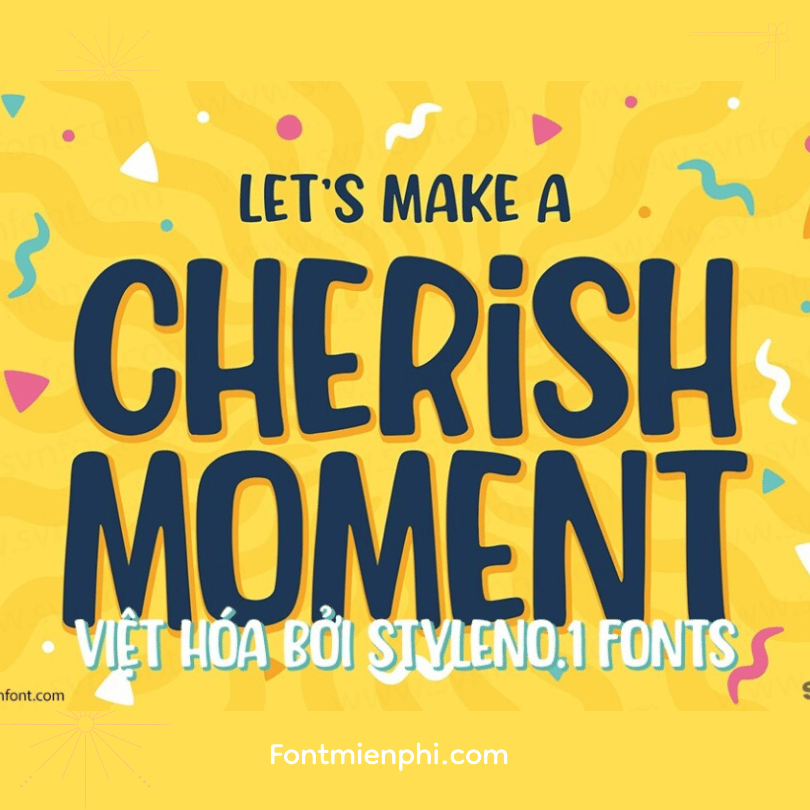
Nguyên Tắc Vàng Trong Phối Font Chữ: Bí Quyết Tạo Sự Hài Hòa và Chuyên Nghiệp
Phối font chữ một cách hài hòa và chuyên nghiệp là yếu tố then chốt để tạo nên một thiết kế ấn tượng và hiệu quả, đồng thời đóng vai trò quan trọng trong cách phối font chữ trong thiết kế, giúp truyền tải thông điệp một cách rõ ràng và thu hút. Việc nắm vững các nguyên tắc phối font chữ không chỉ giúp nâng cao tính thẩm mỹ cho thiết kế, mà còn góp phần xây dựng nhận diện thương hiệu mạnh mẽ và chuyên nghiệp.
Để đạt được sự hài hòa và chuyên nghiệp trong phối font chữ, cần tuân thủ một số nguyên tắc cơ bản. Một trong số đó là sự tương phản. Tương phản không chỉ giúp phân cấp thông tin một cách rõ ràng, mà còn tạo điểm nhấn thị giác, thu hút sự chú ý của người xem. Ví dụ, bạn có thể kết hợp một font serif cổ điển cho tiêu đề với một font sans-serif hiện đại cho nội dung, hoặc sử dụng các font có độ đậm nhạt khác nhau. Tuy nhiên, cần lưu ý tránh sự tương phản quá mức, gây rối mắt và khó đọc.
Tiếp theo, tính dễ đọc là một yếu tố không thể bỏ qua. Dù font chữ có đẹp đến đâu, nếu khó đọc thì thiết kế đó cũng không thể thành công. Chọn font chữ phù hợp với kích thước và khoảng cách dòng, đảm bảo người đọc có thể dễ dàng tiếp thu thông tin. Theo nghiên cứu về trải nghiệm người dùng (UX), một font chữ dễ đọc có thể tăng thời gian người dùng ở lại trang web lên đến 47%. Ví dụ, với website, hãy ưu tiên các font sans-serif như Arial, Helvetica hoặc Open Sans cho phần nội dung chính.
Cuối cùng, sự phù hợp với thương hiệu là một nguyên tắc quan trọng. Font chữ cần thể hiện được cá tính và giá trị của thương hiệu. Một thương hiệu thời trang cao cấp có thể sử dụng các font serif thanh lịch, trong khi một thương hiệu công nghệ trẻ trung có thể chọn các font sans-serif hiện đại và năng động. Việc sử dụng font chữ đồng nhất trên tất cả các kênh truyền thông giúp xây dựng sự nhận diện thương hiệu mạnh mẽ và nhất quán. Ví dụ, Coca-Cola nổi tiếng với font Spencerian Script đặc trưng, tạo nên sự khác biệt và dễ nhận diện trên toàn cầu.
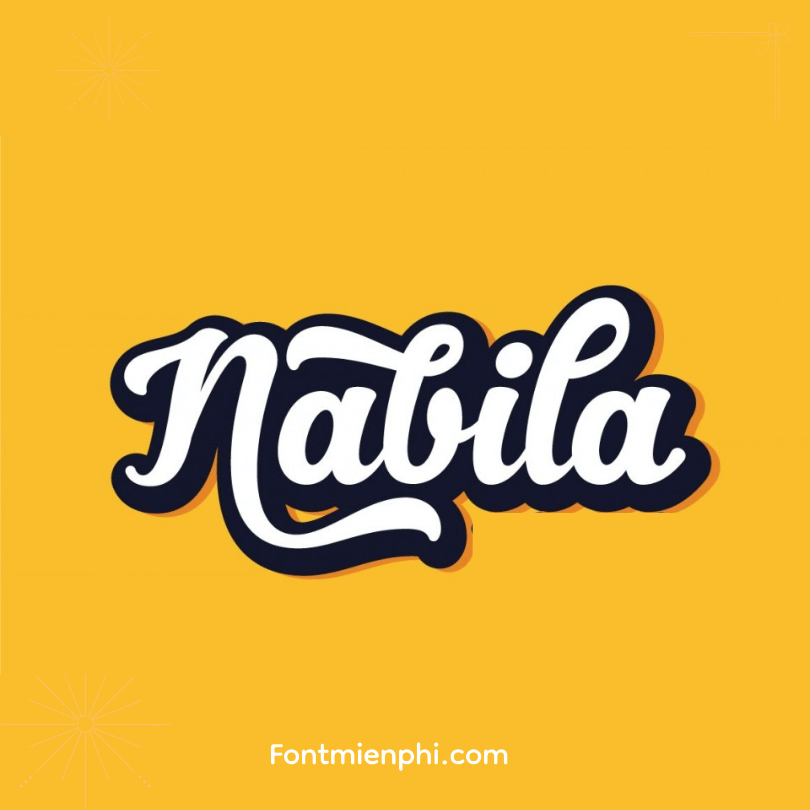
Top Các Cặp Font Chữ Được Ưa Chuộng Năm 2025: Gợi Ý Từ Chuyên Gia Thiết Kế
Để tạo ra một thiết kế ấn tượng, cách phối font chữ trong thiết kế đóng vai trò then chốt, và việc lựa chọn các cặp font chữ phù hợp, đặc biệt những cặp font chữ được ưa chuộng trong năm 2025, sẽ giúp bạn tạo nên sự khác biệt. Việc nắm bắt xu hướng phối font chữ được dự đoán bởi các chuyên gia không chỉ đảm bảo tính thẩm mỹ mà còn giúp truyền tải thông điệp hiệu quả, góp phần vào thành công của dự án thiết kế.
Trong năm 2025, xu hướng phối font chữ sẽ tập trung vào sự cân bằng giữa tính hiện đại và sự dễ đọc, đồng thời thể hiện cá tính riêng của thương hiệu. Thay vì chỉ đơn thuần chọn những font chữ đẹp mắt, các nhà thiết kế sẽ ưu tiên những cặp font chữ có khả năng hỗ trợ lẫn nhau, tạo ra sự hài hòa về mặt thị giác và nâng cao trải nghiệm người dùng. Dưới đây là một số gợi ý cặp font chữ được ưa chuộng năm 2025 từ các chuyên gia:
- Roboto & Roboto Slab: Sự kết hợp giữa một sans-serif (Roboto) và một slab-serif (Roboto Slab) tạo nên sự tương phản tinh tế, phù hợp cho cả tiêu đề và nội dung văn bản. Roboto mang đến sự hiện đại, dễ đọc, trong khi Roboto Slab thêm vào chút cổ điển và mạnh mẽ, giúp thiết kế trở nên thu hút hơn. Ví dụ: Sử dụng Roboto Slab cho tiêu đề và Roboto cho phần nội dung trên website.
- Open Sans & Montserrat: Đây là cặp đôi hoàn hảo cho những thiết kế tối giản, hiện đại. Open Sans, với đường nét thanh mảnh và dễ đọc, thường được sử dụng cho phần thân văn bản. Montserrat, một font sans-serif đậm nét hơn, tạo điểm nhấn ấn tượng cho tiêu đề. Ví dụ: Ứng dụng cặp font này cho các ấn phẩm quảng cáo trực tuyến.
- Playfair Display & Montserrat: Nếu bạn muốn thiết kế của mình mang hơi hướng sang trọng và tinh tế, Playfair Display kết hợp cùng Montserrat là một lựa chọn tuyệt vời. Playfair Display là một font serif với đường nét thanh lịch, thường được dùng cho tiêu đề hoặc logo. Montserrat, với tính linh hoạt cao, dễ dàng kết hợp với Playfair Display trong phần nội dung. Ví dụ: Sử dụng cho các thiết kế liên quan đến thời trang cao cấp hoặc làm đẹp.
- Merriweather & Oswald: Merriweather, một font serif được thiết kế để đọc tốt trên màn hình, là lựa chọn lý tưởng cho phần nội dung dài. Oswald, một font sans-serif với dáng vẻ mạnh mẽ, thường được sử dụng cho tiêu đề hoặc các đoạn văn bản ngắn cần thu hút sự chú ý. Ví dụ: Phù hợp cho các trang blog hoặc tạp chí trực tuyến.
- Poppins & Lato: Cả Poppins và Lato đều là những font sans-serif hiện đại và dễ đọc, nhưng chúng có những đặc điểm riêng biệt giúp tạo nên sự hài hòa khi kết hợp. Poppins có cấu trúc hình học rõ ràng, trong khi Lato mềm mại và thân thiện hơn. Ví dụ: Sử dụng cặp font này cho các ứng dụng di động hoặc giao diện người dùng.
Việc lựa chọn cặp font chữ phù hợp không chỉ dừng lại ở yếu tố thẩm mỹ, mà còn cần xem xét đến tính ứng dụng và khả năng truyền tải thông điệp của thiết kế. Các chuyên gia khuyên rằng nên thử nghiệm nhiều cặp font chữ khác nhau và đánh giá chúng trong ngữ cảnh cụ thể của dự án để đạt được hiệu quả tốt nhất. Bên cạnh đó, việc cập nhật xu hướng phối font chữ mới nhất sẽ giúp bạn tạo ra những thiết kế độc đáo và ấn tượng, bắt kịp với sự thay đổi của thị trường.
Công Cụ Hỗ Trợ Phối Font Chữ: Tiết Kiệm Thời Gian và Nâng Cao Hiệu Quả Thiết Kế
Việc lựa chọn và phối font chữ phù hợp đóng vai trò then chốt trong thiết kế, nhưng quá trình này có thể tốn nhiều thời gian và công sức. May mắn thay, ngày nay có rất nhiều công cụ hỗ trợ phối font chữ ra đời, giúp các nhà thiết kế tiết kiệm thời gian đáng kể và nâng cao hiệu quả thiết kế. Các công cụ này không chỉ đơn thuần gợi ý các cặp font chữ đẹp mắt mà còn cung cấp nhiều tính năng hữu ích khác, hỗ trợ bạn đưa ra những quyết định sáng suốt nhất cho dự án của mình.
Một trong những lợi ích lớn nhất của công cụ phối font là khả năng gợi ý các cặp font chữ hài hòa. Thay vì phải tự mình thử nghiệm hàng trăm sự kết hợp khác nhau, bạn có thể nhanh chóng tìm thấy những phong cách phối font độc đáo và phù hợp với thông điệp mà bạn muốn truyền tải. Ví dụ, Fontjoy sử dụng thuật toán để tạo ra các kết hợp font chữ ngẫu nhiên, giúp bạn khám phá những ý tưởng mới mẻ, trong khi đó, Adobe Fonts cung cấp các bộ sưu tập font chữ được tuyển chọn kỹ lưỡng bởi các chuyên gia.
Ngoài ra, các công cụ hỗ trợ phối font chữ thường đi kèm với các tính năng bổ sung, giúp bạn tinh chỉnh và kiểm tra các lựa chọn của mình. Ví dụ, nhiều công cụ cho phép bạn xem trước các cặp font trong thiết kế thực tế, từ đó đánh giá được tính thẩm mỹ và khả năng đọc của chúng. Fontpair còn cung cấp thông tin chi tiết về tính cách của từng font chữ, giúp bạn chọn được những font phù hợp với tính cách thương hiệu. Một số công cụ thậm chí còn tích hợp chức năng kiểm tra độ tương phản, đảm bảo văn bản của bạn dễ đọc đối với tất cả mọi người.
Dưới đây là một số công cụ hỗ trợ phối font chữ phổ biến mà bạn có thể tham khảo:
- Fontjoy: Tạo ra các kết hợp font chữ ngẫu nhiên dựa trên các tiêu chí bạn chọn.
- Adobe Fonts: Cung cấp bộ sưu tập font chữ chất lượng cao, tích hợp sẵn trong các ứng dụng Adobe Creative Cloud.
- Fontpair: Gợi ý các cặp font chữ đẹp mắt và cung cấp thông tin về tính cách của từng font.
- Google Fonts: Thư viện font chữ miễn phí khổng lồ với nhiều lựa chọn font đa dạng và dễ sử dụng.
- Canva Font Combinations: Cung cấp các mẫu phối font chữ được thiết kế sẵn, phù hợp với nhiều loại thiết kế.
Việt hóa font UTM Androgyne
Việc sử dụng công cụ hỗ trợ phối font chữ không chỉ giúp bạn tiết kiệm thời gian mà còn nâng cao chất lượng thiết kế. Bằng cách tận dụng các tính năng và nguồn tài nguyên mà các công cụ này cung cấp, bạn có thể tạo ra những thiết kế ấn tượng, thu hút và truyền tải thông điệp một cách hiệu quả. Hãy nhớ rằng, việc lựa chọn font chữ phù hợp là một yếu tố quan trọng để tạo nên sự thành công cho bất kỳ dự án thiết kế nào.
Phối Font Chữ Cho Các Loại Hình Thiết Kế Khác Nhau: Website, Logo, Ấn Phẩm In Ấn
Việc lựa chọn và phối font chữ phù hợp đóng vai trò then chốt trong việc truyền tải thông điệp và tạo dựng ấn tượng cho các loại hình thiết kế khác nhau như website, logo, ấn phẩm in ấn. Bởi lẽ, mỗi loại hình thiết kế có những đặc thù riêng, đòi hỏi sự cân nhắc kỹ lưỡng để đảm bảo tính thẩm mỹ, khả năng đọc và hiệu quả truyền thông.
Sự khác biệt giữa các loại hình thiết kế này nằm ở mục đích sử dụng, kích thước hiển thị và đối tượng tiếp nhận. Chẳng hạn, font chữ cho website cần tối ưu hóa trải nghiệm người dùng trên màn hình, trong khi font chữ cho logo cần độc đáo và dễ nhận diện, còn font chữ cho ấn phẩm in ấn cần đảm bảo độ rõ nét và dễ đọc khi in ra. Vì vậy, việc nắm vững các nguyên tắc phối font chữ cho từng loại hình thiết kế là vô cùng quan trọng để tạo ra những sản phẩm thiết kế chuyên nghiệp và hiệu quả.
Phối Font Chữ Cho Website: Tối Ưu Hóa Trải Nghiệm Người Dùng
Đối với website, ưu tiên hàng đầu là khả năng đọc và trải nghiệm người dùng. Điều này có nghĩa là bạn nên chọn các font chữ rõ ràng, dễ đọc trên màn hình và phù hợp với nội dung trang web.
- Font chữ sans-serif (ví dụ: Arial, Helvetica, Open Sans) thường được ưa chuộng cho phần nội dung chính vì tính hiện đại và dễ đọc trên màn hình.
- Font chữ serif (ví dụ: Times New Roman, Georgia) có thể được sử dụng cho tiêu đề hoặc đoạn văn ngắn để tạo điểm nhấn.
- Kích thước font chữ cũng rất quan trọng, nên chọn kích thước vừa đủ lớn để người dùng dễ đọc, đặc biệt trên các thiết bị di động.
- Sự tương phản giữa màu chữ và màu nền cũng cần được chú ý để đảm bảo khả năng đọc tốt nhất.
Font combo thiết kế bất động sản 1 , Sẳn hiệu ứng gradient trong file Ps
Phối Font Chữ Cho Logo: Xây Dựng Nhận Diện Thương Hiệu
Khi thiết kế logo, font chữ đóng vai trò quan trọng trong việc thể hiện bản sắc và giá trị của thương hiệu.
- Hãy chọn font chữ độc đáo, dễ nhận diện và phù hợp với ngành nghề kinh doanh.
- Font chữ có thể mang phong cách hiện đại, cổ điển, mạnh mẽ hoặc tinh tế, tùy thuộc vào thông điệp mà thương hiệu muốn truyền tải.
- Nên hạn chế sử dụng quá nhiều font chữ trong logo (thường chỉ nên dùng 1-2 font) để tránh gây rối mắt và đảm bảo tính nhất quán.
- Cần kiểm tra kỹ lưỡng khả năng hiển thị của font chữ ở các kích thước khác nhau để đảm bảo logo vẫn rõ ràng và sắc nét khi in ấn hoặc hiển thị trên các thiết bị nhỏ.
Phối Font Chữ Cho Ấn Phẩm In Ấn: Đảm Bảo Tính Rõ Ràng và Thẩm Mỹ
Đối với ấn phẩm in ấn (ví dụ: tờ rơi, brochure, sách), yếu tố quan trọng là độ rõ nét và dễ đọc khi in ra.
- Font chữ serif thường được ưu tiên cho phần nội dung chính vì giúp mắt dễ dàng nhận diện các ký tự.
- Font chữ sans-serif có thể được sử dụng cho tiêu đề hoặc các đoạn văn ngắn để tạo sự tương phản.
- Cần chú ý đến khoảng cách giữa các dòng và các chữ cái để đảm bảo khả năng đọc tốt nhất.
- Chọn màu chữ và màu nền phù hợp để tạo sự hài hòa và tránh gây mỏi mắt cho người đọc.
- Đảm bảo độ phân giải của font chữ đủ cao để khi in ra không bị nhòe hoặc vỡ nét.
Tóm lại, việc phối font chữ hiệu quả cho các loại hình thiết kế khác nhau đòi hỏi sự am hiểu về các nguyên tắc thiết kế, đặc tính của từng loại font chữ và mục đích sử dụng của sản phẩm. Bằng cách lựa chọn và kết hợp các font chữ một cách khéo léo, bạn có thể tạo ra những thiết kế ấn tượng, chuyên nghiệp và truyền tải thông điệp một cách hiệu quả nhất.
Những Lỗi Thường Gặp Khi Phối Font Chữ và Cách Khắc Phục
Trong hành trình cách phối font chữ trong thiết kế, việc mắc phải những lỗi sai là điều khó tránh khỏi, nhưng nhận biết và khắc phục chúng lại là yếu tố then chốt để đạt đến thành công. Để tránh những sai lầm đáng tiếc, hãy cùng điểm qua những lỗi phối font chữ phổ biến và tìm hiểu cách khắc phục chúng, từ đó nâng cao chất lượng thiết kế của bạn.
Một trong những lỗi cơ bản nhất là sử dụng quá nhiều font chữ. Việc lạm dụng số lượng font chữ trong một thiết kế tạo ra sự rối mắt, thiếu chuyên nghiệp và phá vỡ tính thẩm mỹ tổng thể. Theo nguyên tắc chung, chỉ nên sử dụng tối đa 2-3 font chữ khác nhau trong một thiết kế.
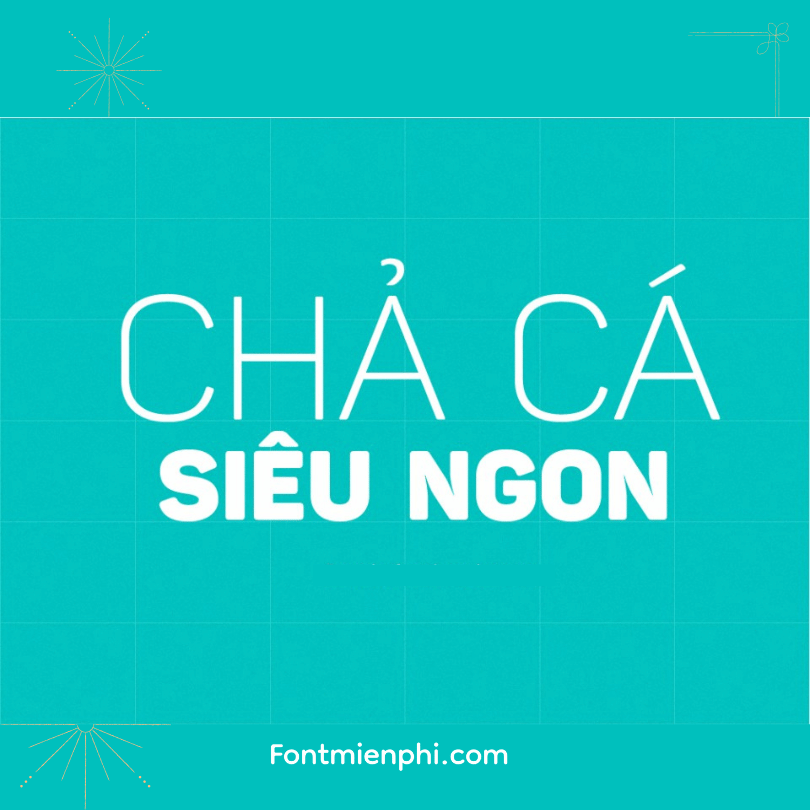
Để khắc phục lỗi này, hãy tuân thủ những nguyên tắc sau:
- Giới hạn số lượng font: Chọn tối đa 2-3 font chữ khác nhau cho một dự án thiết kế.
- Xác định mục đích sử dụng: Mỗi font chữ nên có một vai trò cụ thể, ví dụ: một font cho tiêu đề, một font cho nội dung chính, và một font cho các yếu tố phụ.
- Tạo sự tương phản: Chọn các font chữ có sự khác biệt rõ rệt về kiểu dáng, độ đậm, hoặc chiều cao x để tạo sự tương phản và thu hút sự chú ý.
Một lỗi khác thường gặp là sử dụng các font chữ quá giống nhau. Điều này dẫn đến sự nhàm chán, đơn điệu và không tạo được điểm nhấn cho thiết kế. Mặc dù tính nhất quán quan trọng, nhưng sự khác biệt tinh tế lại tạo nên sự hấp dẫn thị giác.
Để tránh lỗi này, bạn có thể áp dụng các biện pháp sau:
- Chọn font chữ từ các họ khác nhau: Kết hợp một font serif (có chân) với một font sans-serif (không chân) để tạo sự tương phản.
- Thay đổi độ đậm (font weight): Sử dụng các biến thể khác nhau của cùng một font chữ (ví dụ: Regular, Bold, Italic) để tạo sự phân cấp và nhấn mạnh.
- Chú ý đến khoảng cách (letter spacing): Điều chỉnh khoảng cách giữa các chữ cái để tạo sự khác biệt và tăng tính dễ đọc.
Ngoài ra, bỏ qua ngữ cảnh và đối tượng mục tiêu cũng là một sai lầm nghiêm trọng. Mỗi dự án thiết kế đều hướng đến một đối tượng cụ thể và truyền tải một thông điệp nhất định. Việc chọn font chữ không phù hợp với ngữ cảnh hoặc đối tượng mục tiêu sẽ làm giảm hiệu quả truyền thông và gây khó khăn cho người xem. Ví dụ, một font chữ quá trang trọng có thể không phù hợp cho một trang web dành cho trẻ em.
Để khắc phục lỗi này, hãy:
- Nghiên cứu đối tượng mục tiêu: Tìm hiểu về sở thích, thói quen và đặc điểm của đối tượng mà bạn muốn tiếp cận.
- Xác định thông điệp chính: Lựa chọn font chữ thể hiện được tinh thần và giá trị của thông điệp mà bạn muốn truyền tải.
- Tham khảo các ví dụ thiết kế thành công: Học hỏi từ những dự án đã được chứng minh là hiệu quả trong việc sử dụng font chữ.
Cuối cùng, không kiểm tra kỹ lưỡng trên các thiết bị khác nhau cũng là một thiếu sót cần tránh. Font chữ hiển thị khác nhau trên các màn hình, trình duyệt và hệ điều hành khác nhau. Một font chữ trông đẹp trên máy tính của bạn có thể bị vỡ, mờ hoặc khó đọc trên điện thoại di động.
Để đảm bảo tính nhất quán và chuyên nghiệp, hãy:
- Kiểm tra trên nhiều thiết bị: Xem trước thiết kế của bạn trên các thiết bị khác nhau (máy tính, điện thoại, máy tính bảng) để đảm bảo font chữ hiển thị đúng như mong muốn.
- Sử dụng các font chữ web an toàn: Lựa chọn các font chữ phổ biến, được hỗ trợ rộng rãi trên các trình duyệt và hệ điều hành khác nhau. Google Fonts là một nguồn tài nguyên tuyệt vời để tìm kiếm các font chữ web miễn phí và chất lượng cao.
- Tối ưu hóa font chữ cho web: Sử dụng các kỹ thuật như font-face và woff2 để đảm bảo font chữ được tải nhanh và hiển thị chính xác trên các trình duyệt web.
Xu Hướng Phối Font Chữ Trong Thiết Kế Năm 2025: Bắt Kịp Sự Đổi Mới
Năm 2025 hứa hẹn những làn gió mới trong xu hướng phối font chữ, đòi hỏi các nhà thiết kế phải liên tục cập nhật và bắt kịp sự đổi mới để tạo ra những sản phẩm ấn tượng, thu hút. Việc nắm bắt những xu hướng này không chỉ giúp tối ưu hóa cách phối font chữ trong thiết kế mà còn là chìa khóa để nâng cao tính cạnh tranh và khẳng định dấu ấn cá nhân trong thị trường đầy biến động.
Vậy, những xu hướng nào sẽ “làm mưa làm gió” trong năm 2025 và cách chúng ta có thể áp dụng chúng một cách hiệu quả?
- Sự trỗi dậy của font chữ biến thể (Variable Fonts): Variable Fonts cho phép điều chỉnh linh hoạt các thuộc tính của font như độ dày, độ rộng, độ nghiêng, tạo ra vô vàn biến thể từ một font gốc. Điều này giúp tiết kiệm dung lượng, tăng tốc độ tải trang web và mở ra khả năng sáng tạo vô tận cho các nhà thiết kế. Dự kiến vào năm 2025, việc sử dụng font chữ biến thể sẽ trở nên phổ biến hơn bao giờ hết, đặc biệt trong thiết kế web và ứng dụng di động, nơi tốc độ và tính linh hoạt là yếu tố then chốt.
- Kết hợp táo bạo giữa Serif và Sans-serif: Thay vì tuân theo quy tắc truyền thống, các nhà thiết kế ngày càng ưa chuộng việc kết hợp font Serif và font Sans-serif một cách táo bạo và độc đáo. Sự tương phản giữa hai loại font này tạo ra hiệu ứng thị giác mạnh mẽ, thu hút sự chú ý của người xem và truyền tải thông điệp một cách hiệu quả. Ví dụ, một tiêu đề sử dụng font Serif cổ điển kết hợp với phần thân văn bản sử dụng font Sans-serif hiện đại có thể tạo ra sự cân bằng giữa tính trang trọng và tính thân thiện.
- Ưu tiên tính dễ đọc và khả năng tiếp cận: Trong bối cảnh nội dung số ngày càng trở nên quan trọng, tính dễ đọc và khả năng tiếp cận là những yếu tố được ưu tiên hàng đầu trong thiết kế font chữ. Các font chữ rõ ràng, đơn giản, có khoảng cách rộng rãi giữa các chữ cái và dòng chữ sẽ giúp người đọc dễ dàng tiếp thu thông tin, đặc biệt trên các thiết bị di động có màn hình nhỏ. Ngoài ra, việc lựa chọn font chữ hỗ trợ nhiều ngôn ngữ và ký tự đặc biệt cũng là một yếu tố quan trọng để đảm bảo khả năng tiếp cận cho mọi đối tượng người dùng.
- Phong cách tối giản (Minimalism) lên ngôi: Phong cách tối giản tiếp tục thống trị trong thiết kế nói chung và thiết kế font chữ nói riêng. Các font chữ đơn giản, không cầu kỳ, tập trung vào chức năng và hiệu quả truyền tải thông điệp sẽ được ưa chuộng. Sự tối giản không chỉ giúp tạo ra một thiết kế thanh lịch, hiện đại mà còn giúp giảm thiểu sự xao nhãng và tập trung sự chú ý của người xem vào nội dung chính.
- Sự ảnh hưởng của thiết kế hoài cổ (Retro Design): Bên cạnh phong cách tối giản, thiết kế hoài cổ cũng đang dần trở lại, mang theo những font chữ mang đậm dấu ấn của quá khứ. Các font chữ lấy cảm hứng từ những năm 70, 80 với những đường nét độc đáo, màu sắc tươi sáng sẽ được sử dụng để tạo ra những thiết kế mang tính cá nhân và hoài niệm. Tuy nhiên, cần lưu ý kết hợp font chữ hoài cổ một cách khéo léo với các yếu tố hiện đại để tránh tạo ra một thiết kế lỗi thời và thiếu chuyên nghiệp.
Đừng bỏ lỡ cơ hội ‘nâng cấp’ thiết kế của bạn! Tìm hiểu ngay những xu hướng phối font chữ độc đáo, giúp bạn tạo ra những tác phẩm ấn tượng và khác biệt.
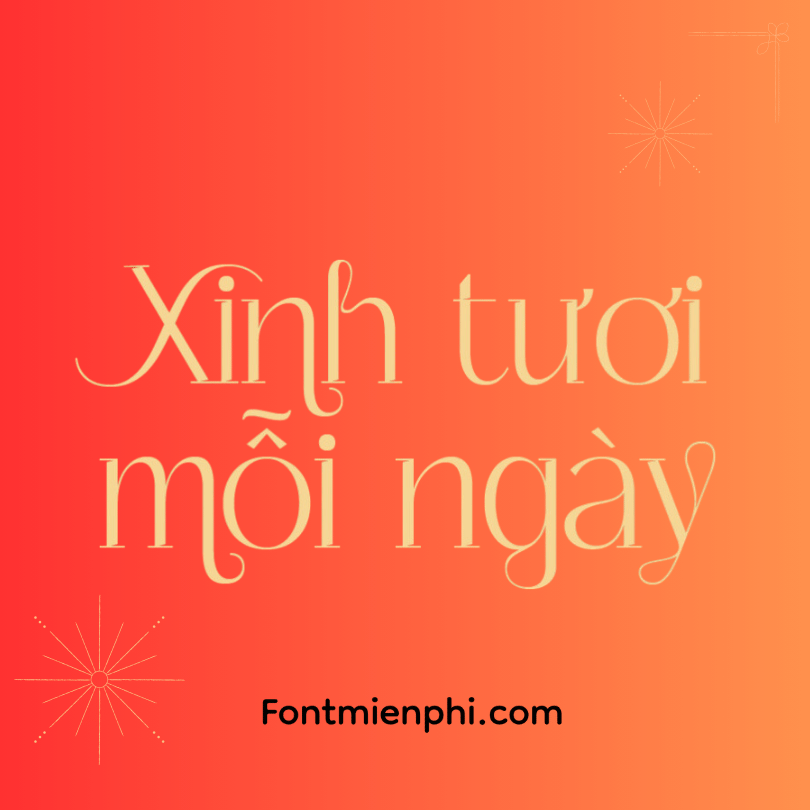
Nguồn Cảm Hứng Phối Font Chữ: Khám Phá Các Dự Án Thiết Kế Thành Công
Việc tìm kiếm nguồn cảm hứng đóng vai trò quan trọng trong quá trình sáng tạo cách phối font chữ trong thiết kế, giúp các nhà thiết kế có thêm ý tưởng và tạo ra những tác phẩm ấn tượng. Khám phá các dự án thiết kế thành công không chỉ giúp bạn học hỏi kinh nghiệm mà còn mở ra những hướng đi mới trong việc lựa chọn và kết hợp font chữ. Những dự án này thường là minh chứng rõ ràng nhất cho thấy sự kết hợp hài hòa giữa các yếu tố typography, tạo nên một tổng thể thị giác thu hút và truyền tải thông điệp hiệu quả.
Để phối font chữ một cách hiệu quả, việc nghiên cứu các dự án thiết kế đã thành công là một bước đi thông minh. Dưới đây là một số khía cạnh bạn có thể khai thác từ các dự án này:
- Phân tích lựa chọn font chữ: Xem xét kỹ lưỡng tại sao nhà thiết kế lại chọn những font chữ cụ thể cho dự án. Font chữ đó có phù hợp với phong cách và thông điệp của thương hiệu hay không? Ví dụ, một thương hiệu thời trang cao cấp có thể sử dụng font serif thanh lịch để thể hiện sự sang trọng, trong khi một công ty công nghệ có thể chọn font sans-serif hiện đại để tạo cảm giác đổi mới.
- Nghiên cứu cách kết hợp font chữ: Chú ý đến cách các font chữ khác nhau được kết hợp với nhau. Font chữ nào được sử dụng cho tiêu đề, font chữ nào được sử dụng cho nội dung chính? Sự tương phản giữa các font chữ có tạo ra sự cân bằng và thu hút thị giác hay không? Một ví dụ điển hình là sự kết hợp giữa một font serif cổ điển cho tiêu đề và một font sans-serif đơn giản cho phần thân văn bản, tạo ra sự tương phản rõ ràng và dễ đọc.
- Đánh giá bố cục và cách sử dụng typography: Quan sát cách font chữ được sử dụng trong bố cục tổng thể của thiết kế. Kích thước, khoảng cách và màu sắc của font chữ có được sử dụng một cách hiệu quả để tạo ra sự nhấn mạnh và hướng dẫn người xem hay không? Ví dụ, việc sử dụng kích thước font chữ lớn hơn cho tiêu đề và sử dụng màu sắc tương phản có thể thu hút sự chú ý của người xem và giúp họ dễ dàng nắm bắt thông tin quan trọng.
- Tìm hiểu về ngành và đối tượng mục tiêu: Xem xét ngành mà dự án thiết kế phục vụ và đối tượng mục tiêu mà nó hướng đến. Font chữ được sử dụng có phù hợp với đặc điểm của ngành và sở thích của đối tượng mục tiêu hay không? Ví dụ, một dự án thiết kế cho một sản phẩm dành cho trẻ em có thể sử dụng font chữ vui nhộn và màu sắc tươi sáng, trong khi một dự án thiết kế cho một dịch vụ tài chính có thể sử dụng font chữ nghiêm túc và màu sắc trang nhã.
Một số dự án thiết kế thành công mà bạn có thể tham khảo để lấy cảm hứng phối font chữ bao gồm:
- Thiết kế website của Apple: Apple nổi tiếng với phong cách thiết kế tối giản và hiện đại. Họ thường sử dụng font San Francisco trên các sản phẩm và trang web của mình, tạo ra sự đồng nhất và dễ đọc.
- Logo của Coca-Cola: Logo của Coca-Cola là một biểu tượng mang tính biểu tượng với font Spencerian Script độc đáo. Font chữ này thể hiện sự cổ điển, thân thiện và dễ nhận biết.
- Bìa sách của Penguin Books: Penguin Books đã tạo ra một phong cách thiết kế bìa sách đặc trưng với font Gill Sans. Font chữ này mang đến sự đơn giản, thanh lịch và hiện đại.
Bằng cách nghiên cứu và phân tích các dự án thiết kế thành công, bạn sẽ có thêm kiến thức và cảm hứng để lựa chọn và phối font chữ một cách hiệu quả, tạo ra những thiết kế ấn tượng và truyền tải thông điệp một cách rõ ràng.